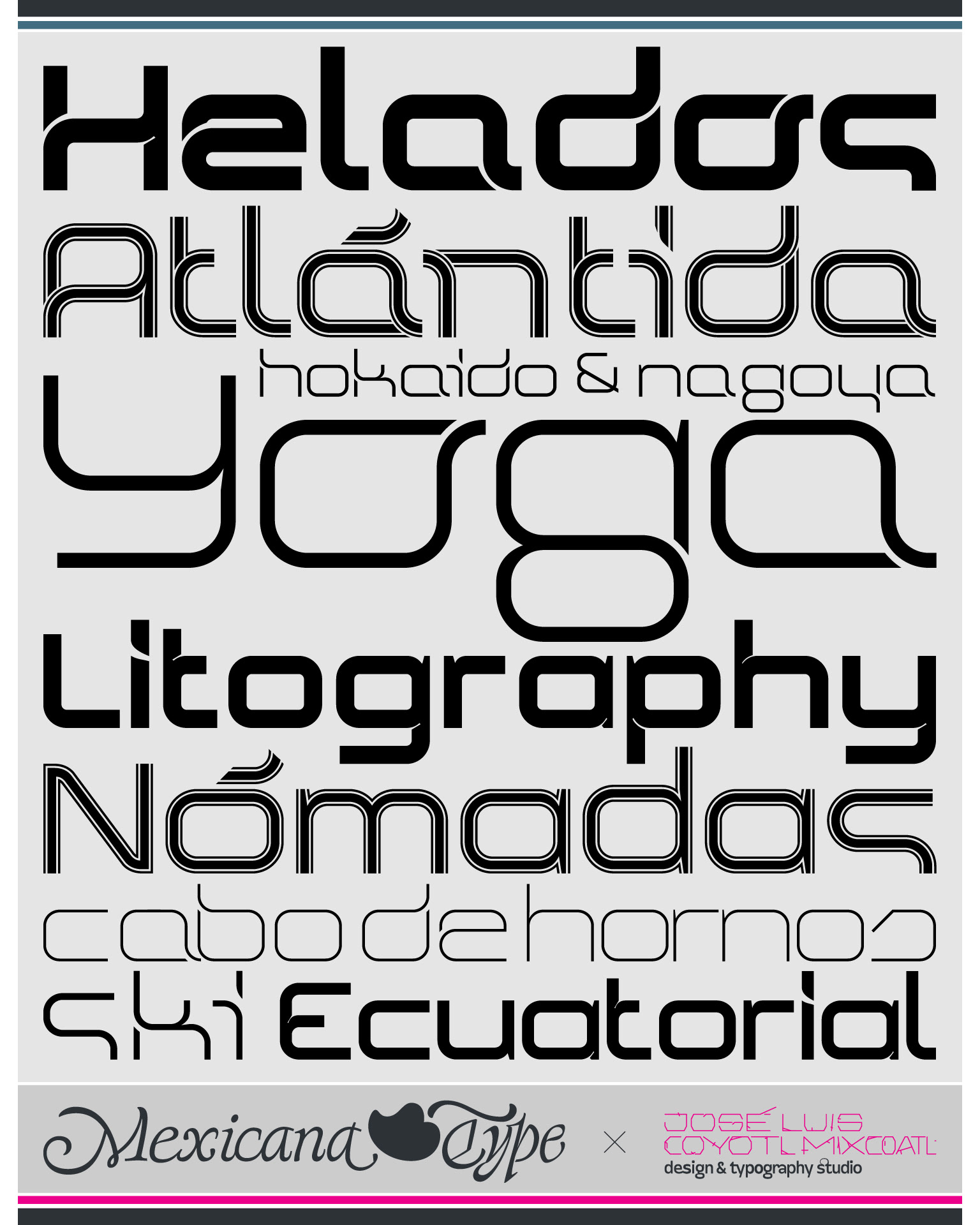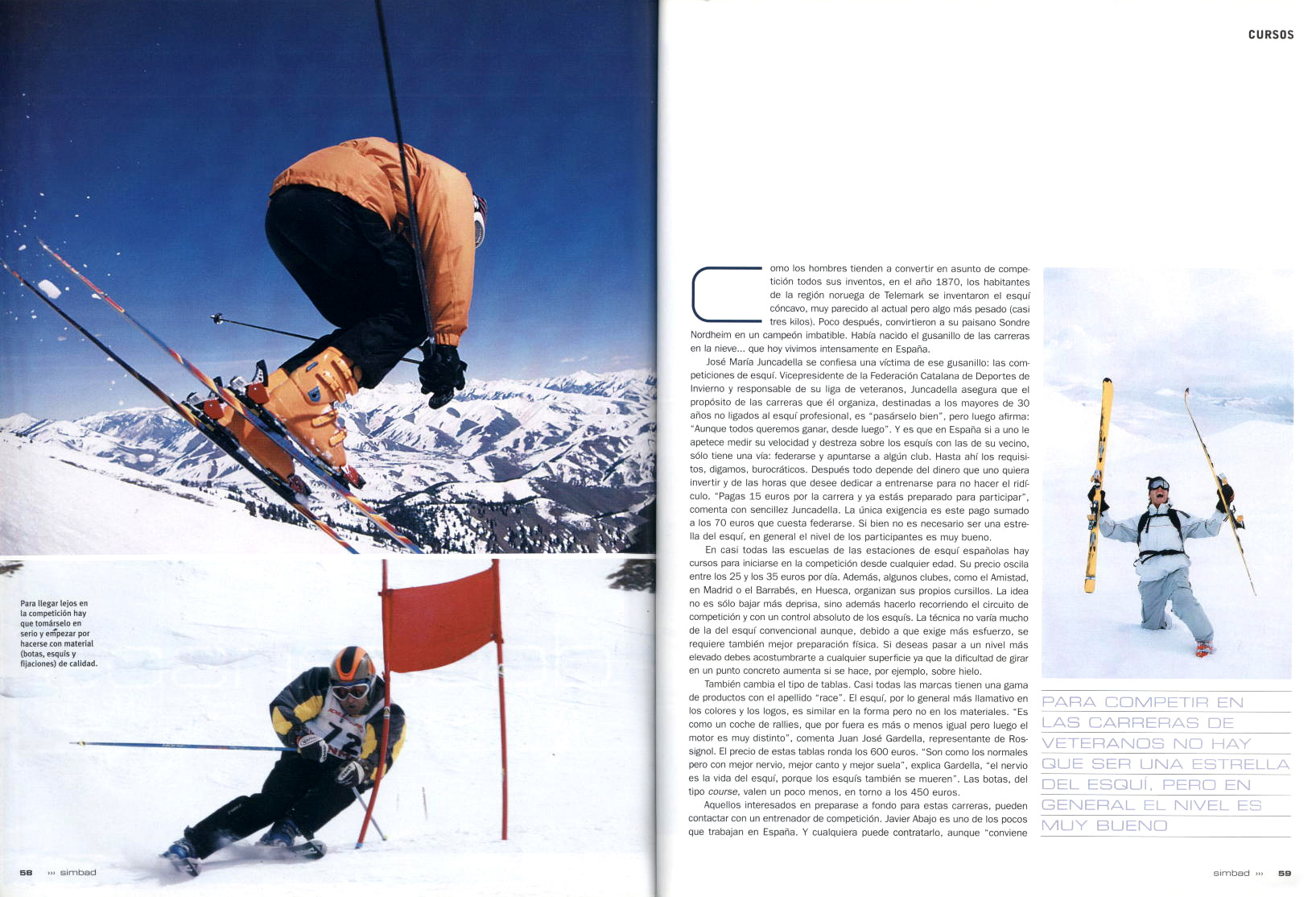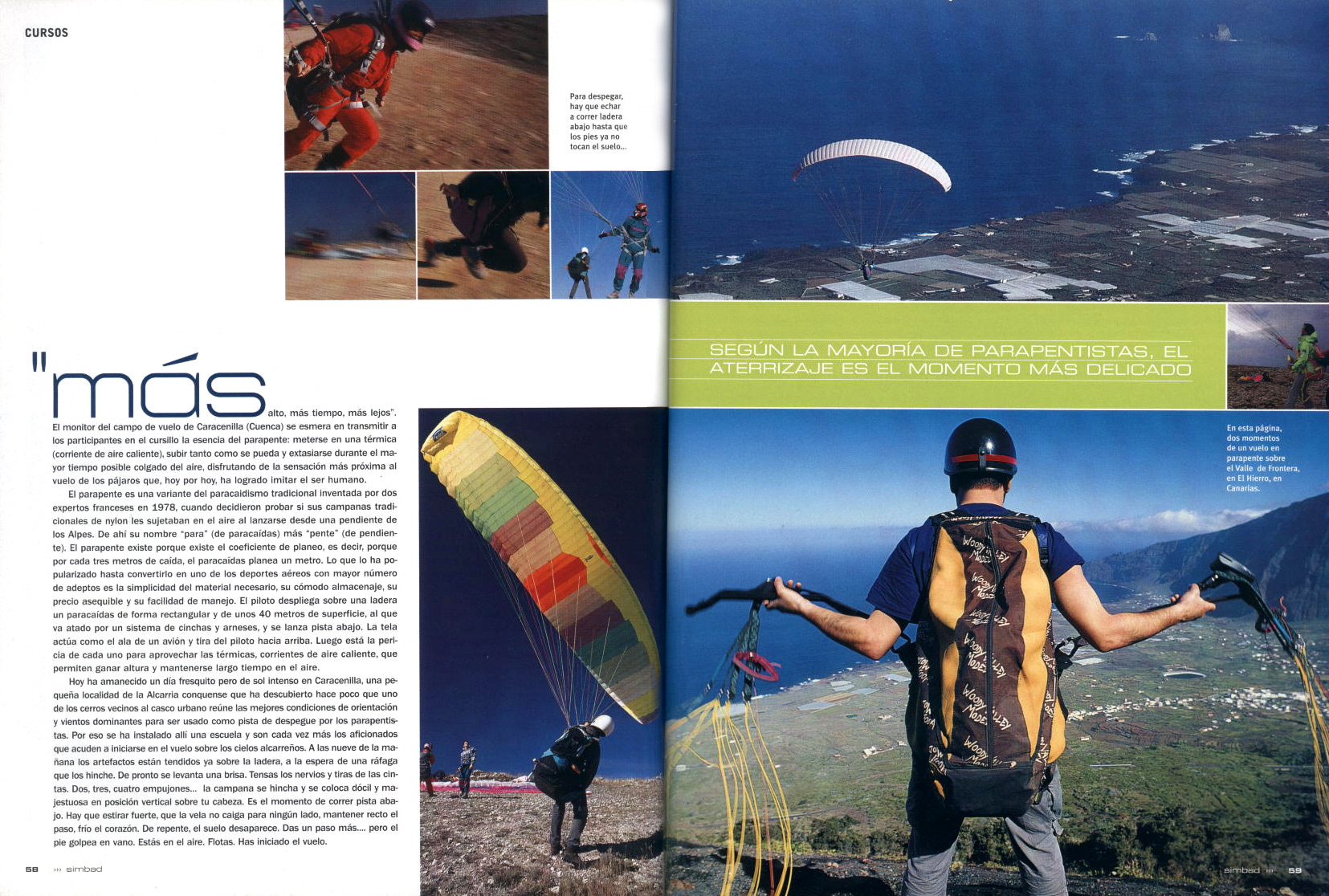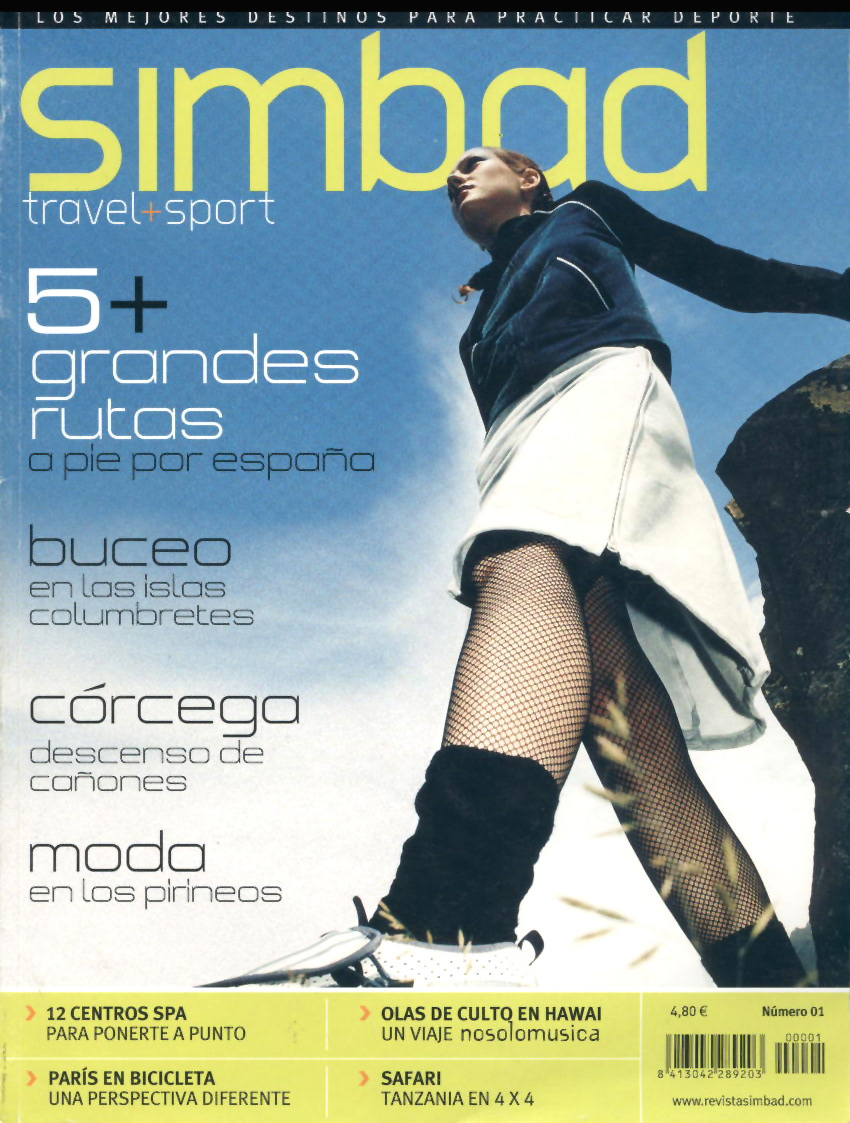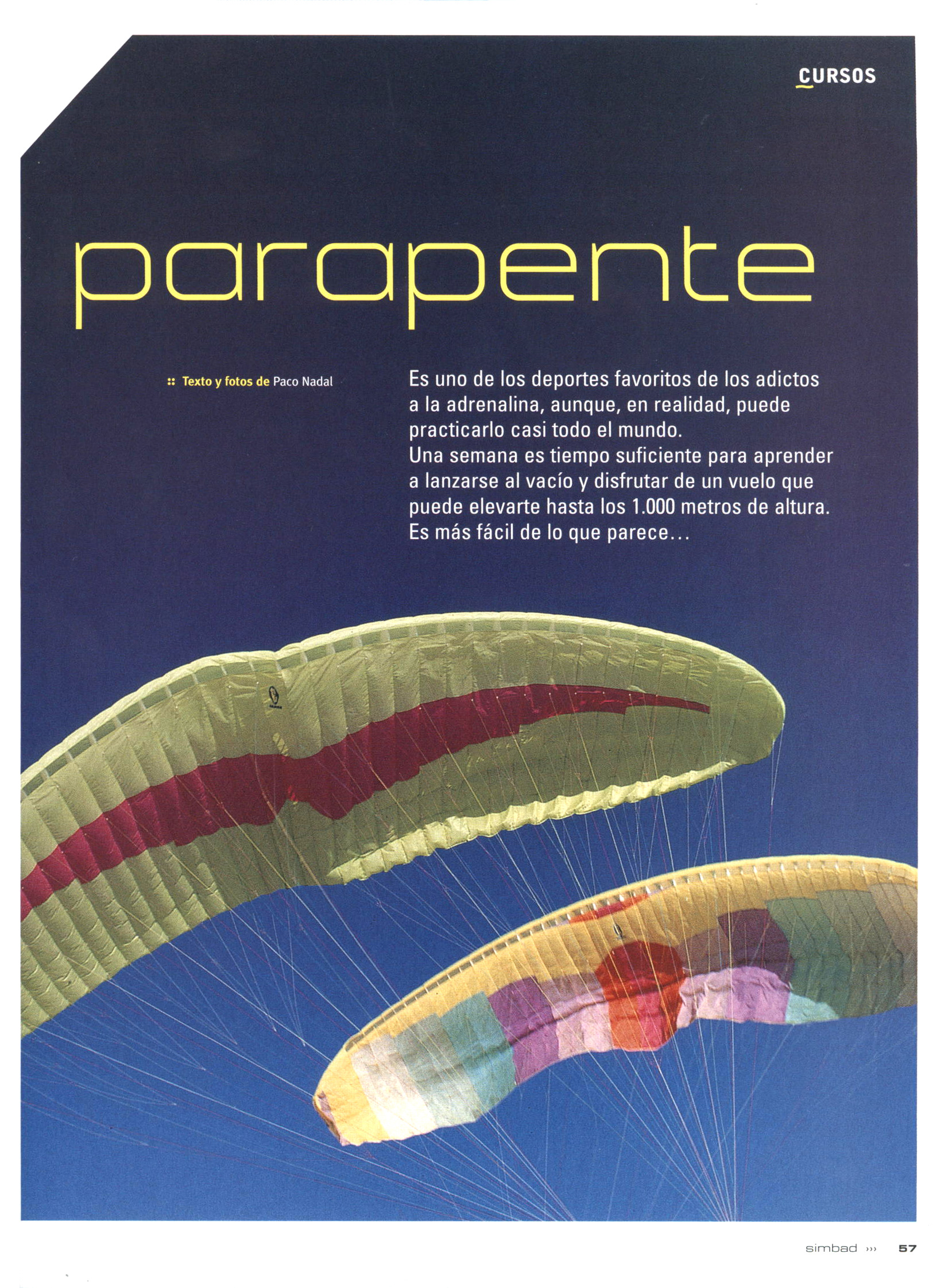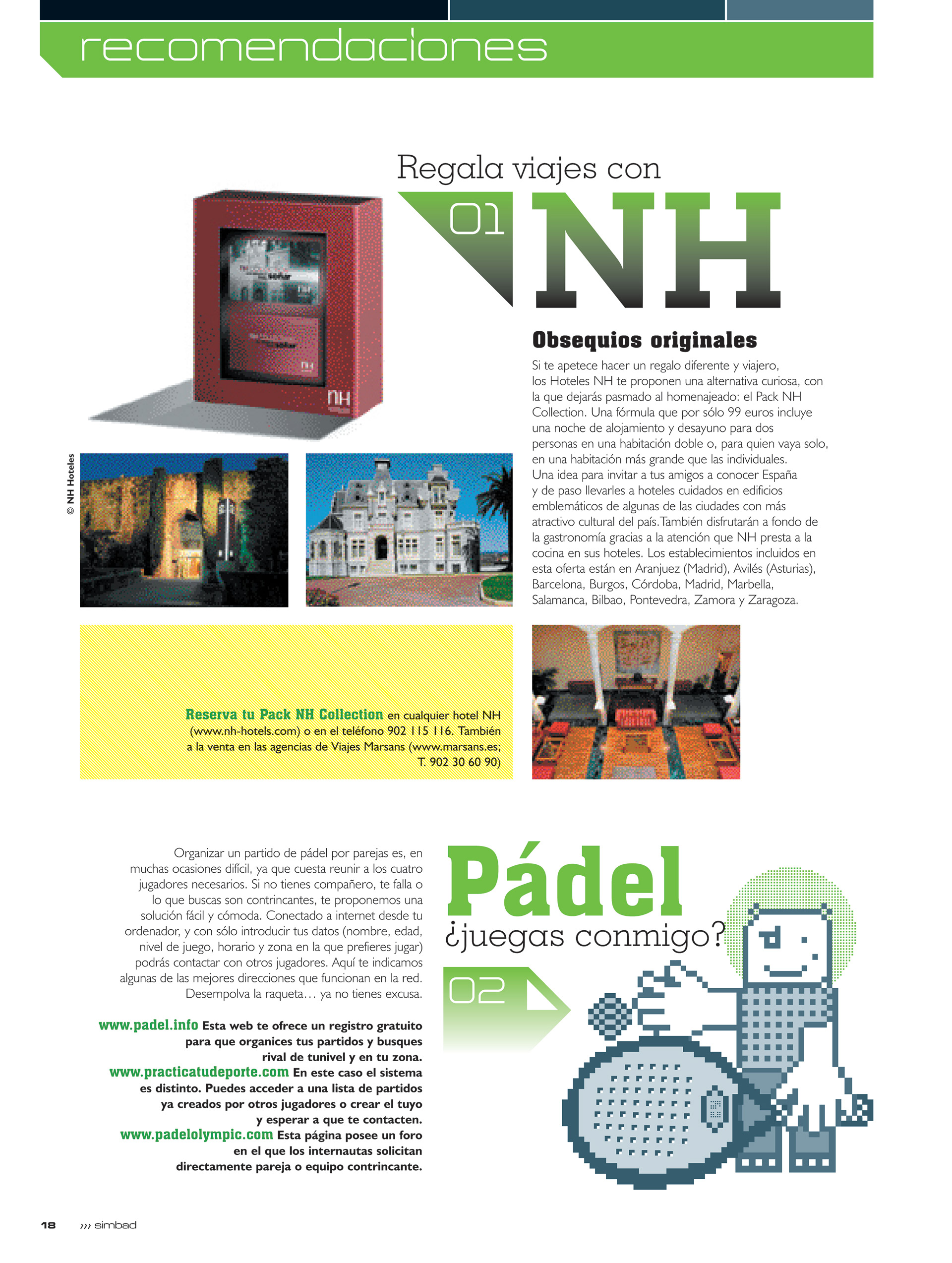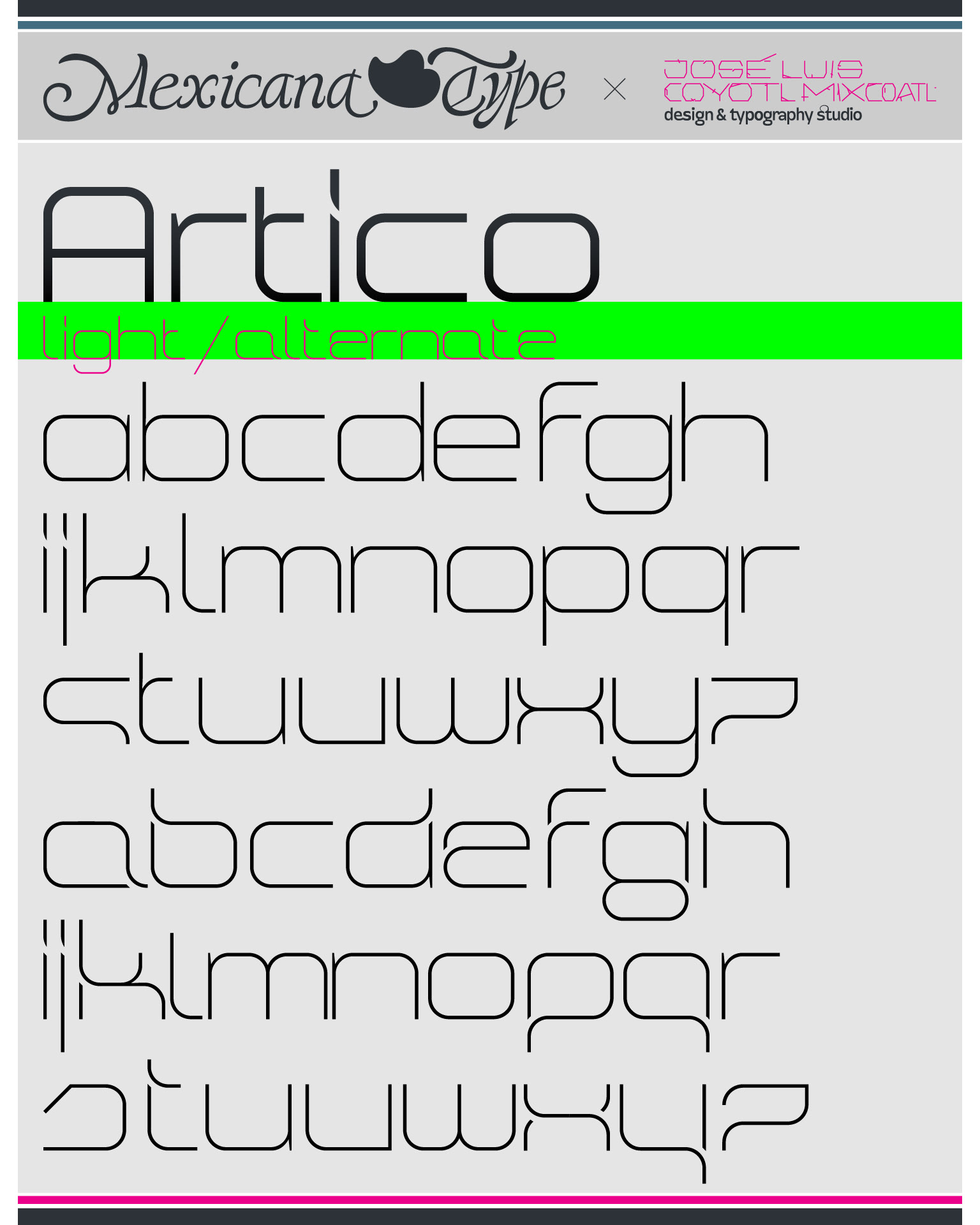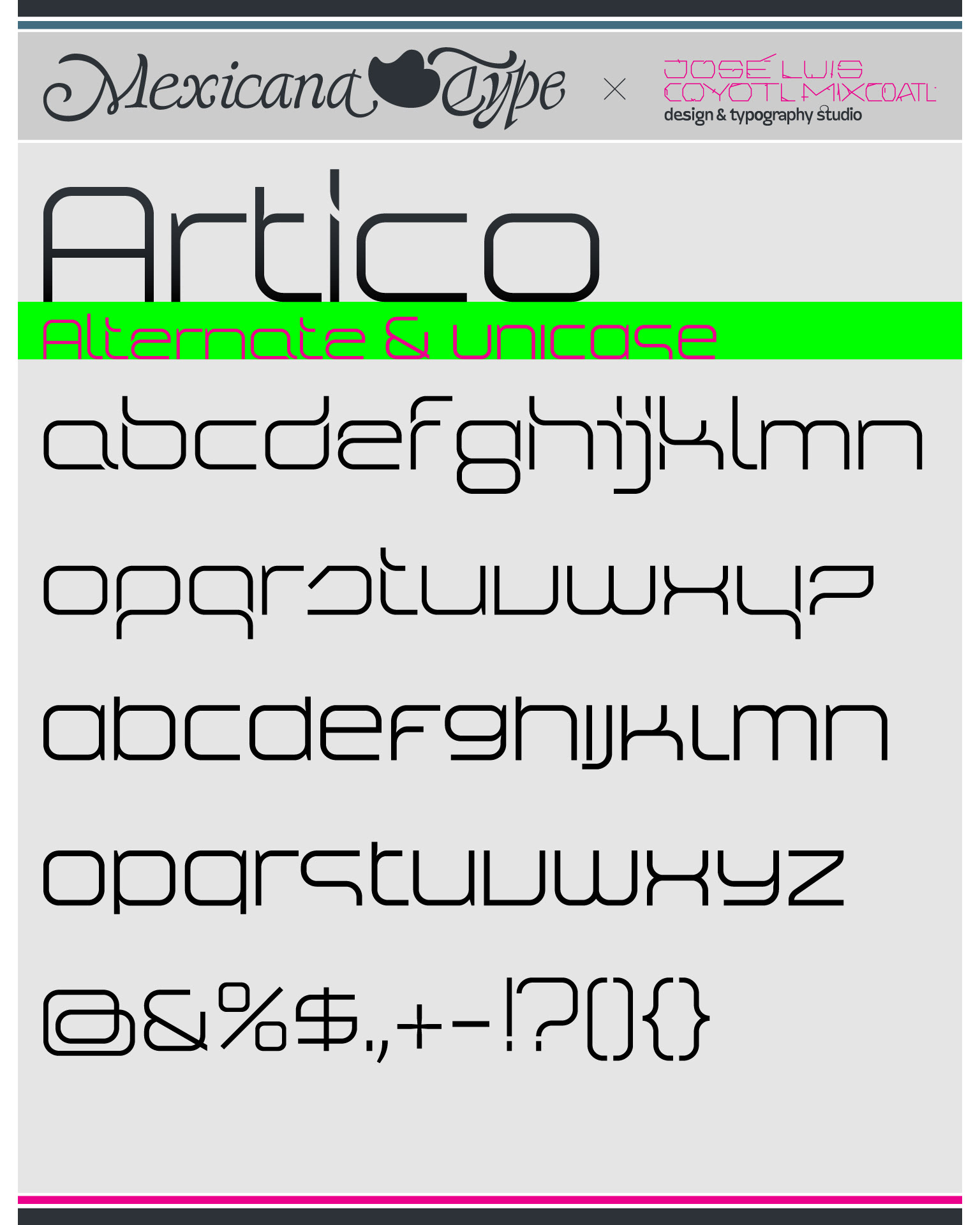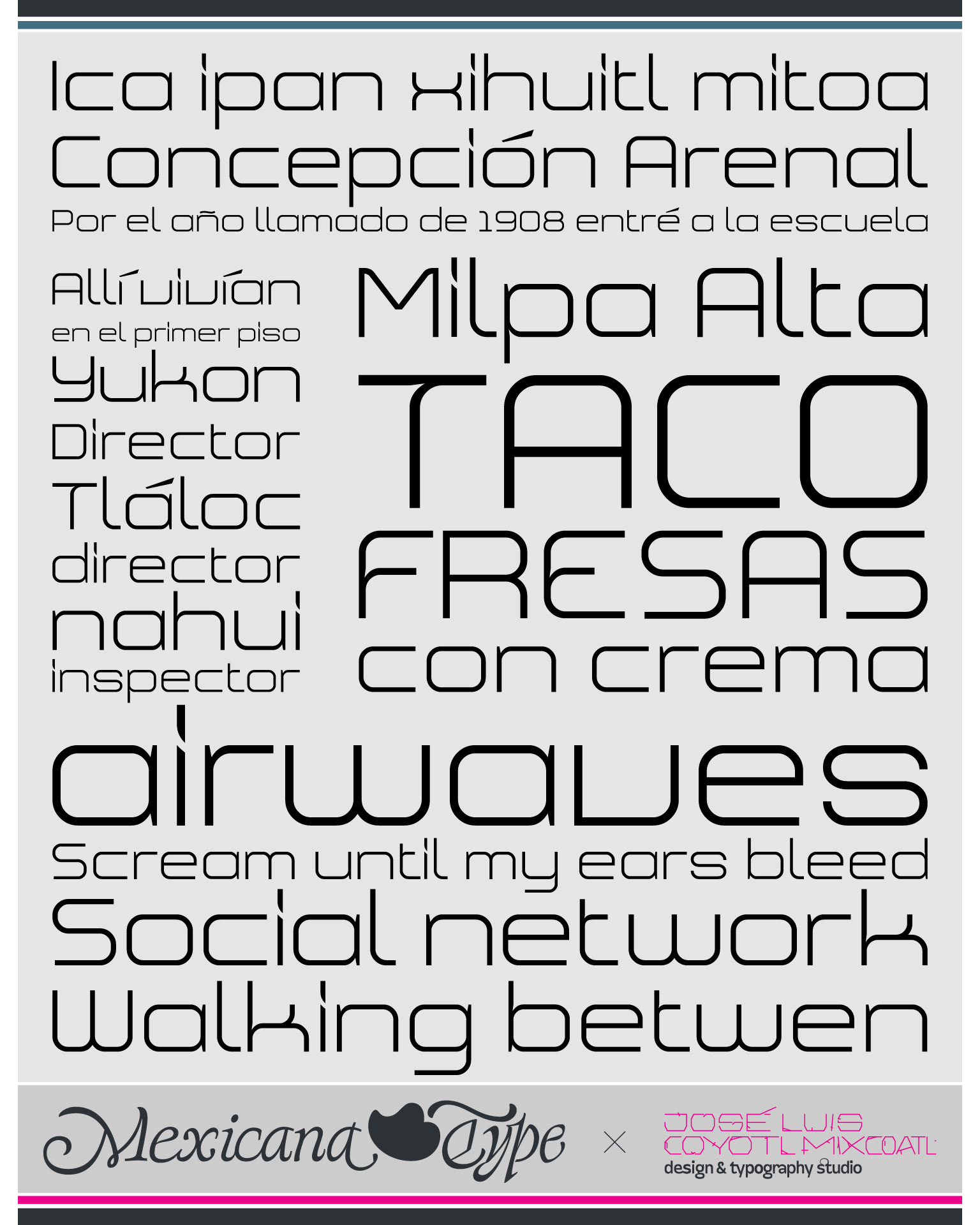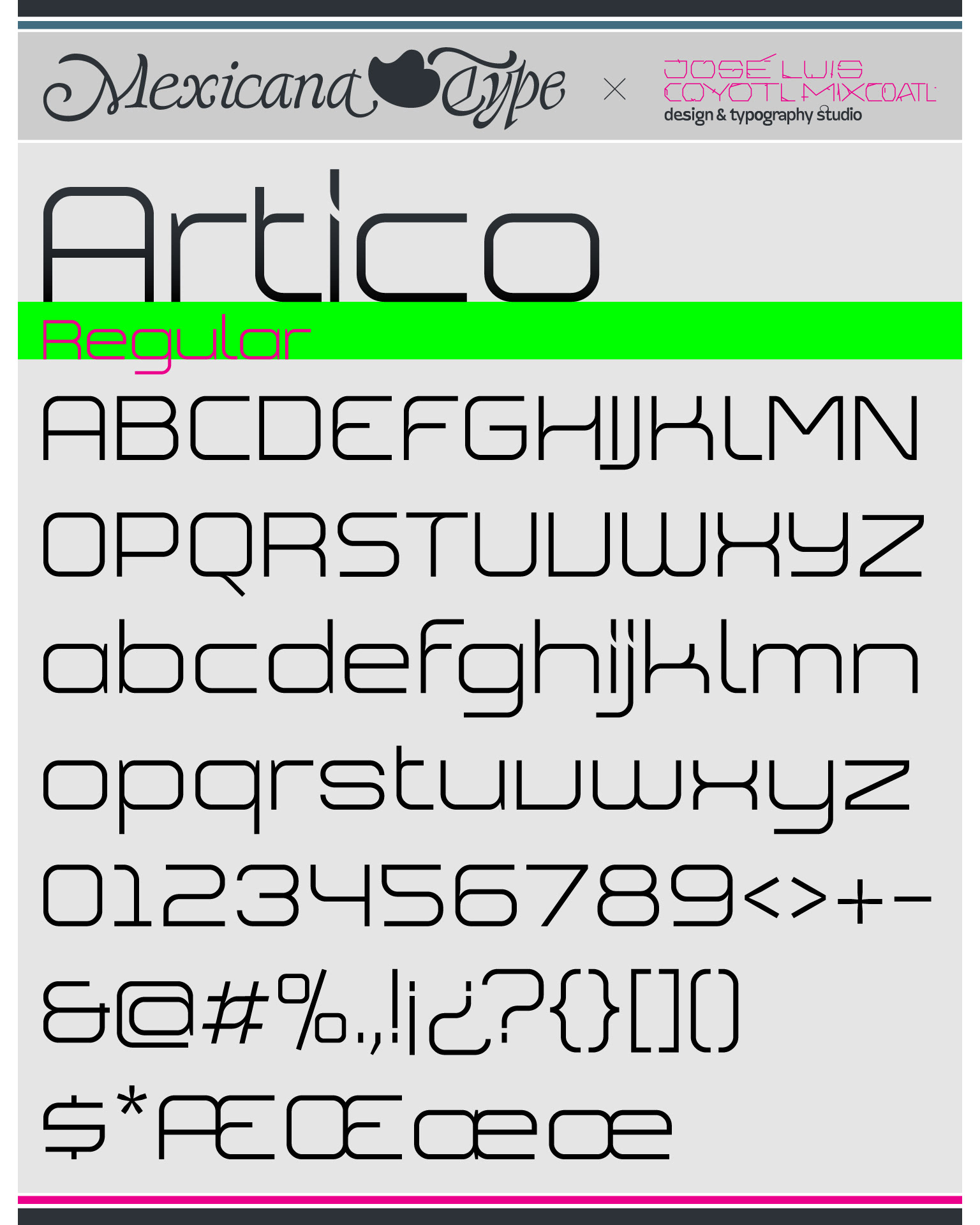
Simbad. Travel+Sports
Custom Type para revista
Ártico es un paquete de tipografías personalizadas para titulares y títulos de la revista española Simbad Travel+ Sports. Al formar parte del equipo de diseño de la revista, me permitió ver y hacer las adecuaciones necesarias a las necesidades de la revista en su entorno editorial y los criterios de estilos gráficos y diseño integral de las secciones y el conjunto de la revista me guiaron para desarrollar diferentes grosores de trazo, así como el ancho del cuerpo de texto, que fueron Light, Regular, Alternates y Dingbats.
La familia tipográfica fue diseñada en 2003 junto al equipo del Estudio La Fe Ciega, en la Ciudad de México.